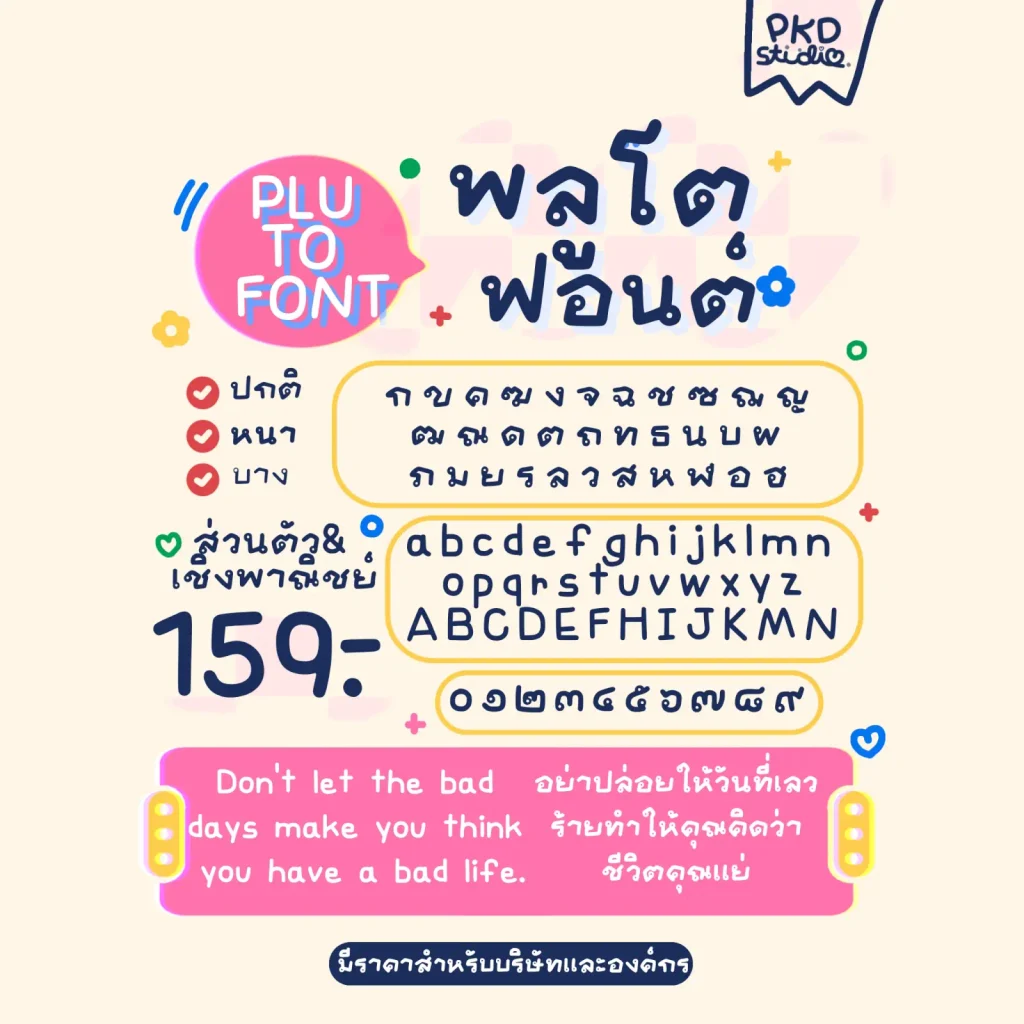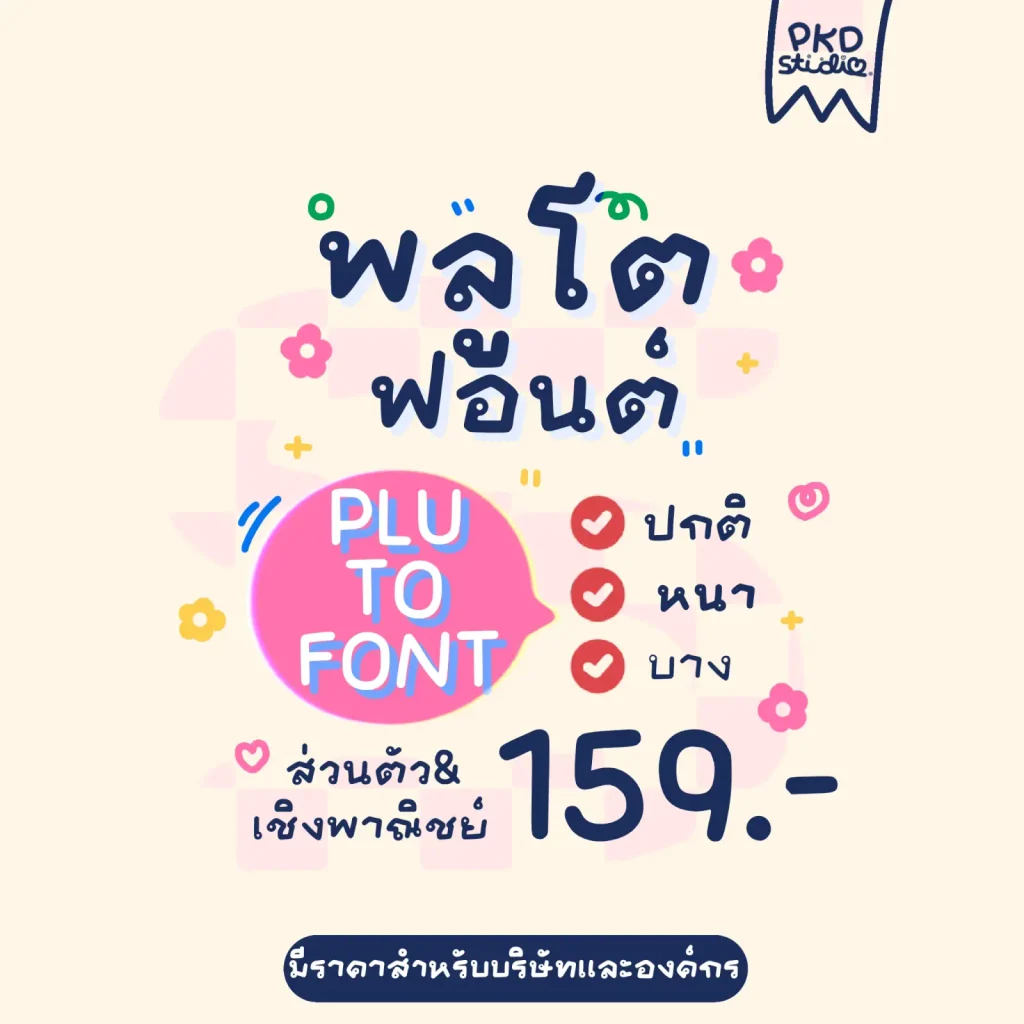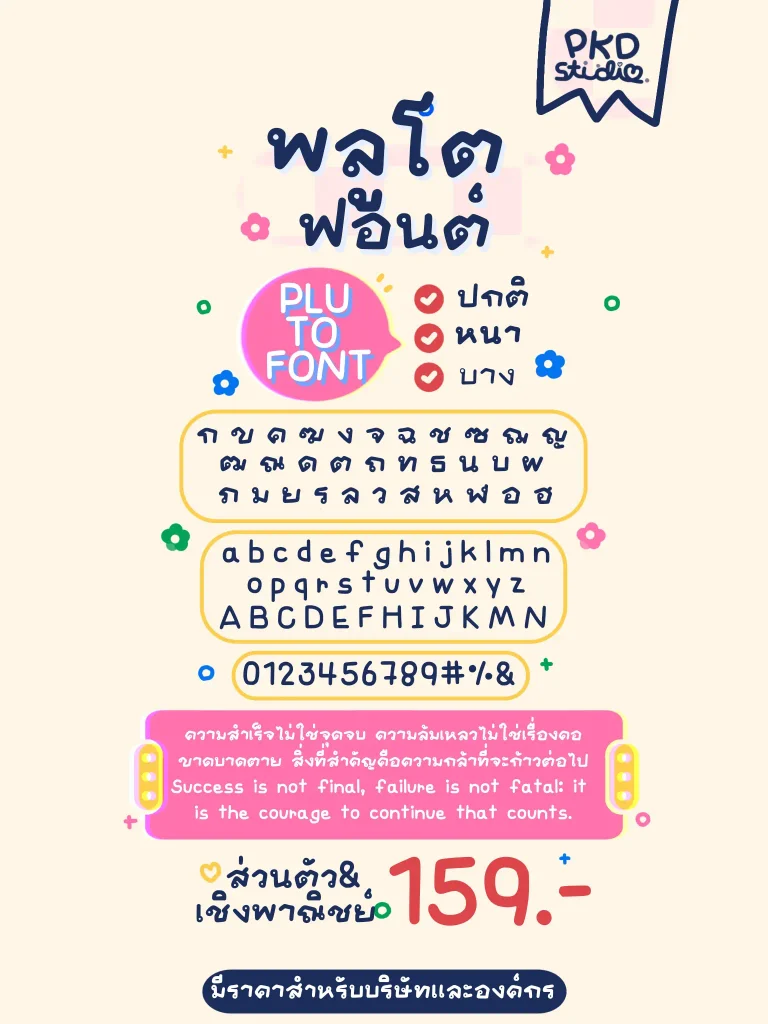
พลูโตฟอนต์ (PKD PLUTO) – ฟอนต์ลายมือน่ารัก สดใส เป็นกันเอง เหมาะสำหรับงานคอนเทนต์ โพสต์โซเชียล สติกเกอร์ คาเฟ่ และงานออกแบบทั่วไป
- รองรับภาษาไทย ภาษาอังกฤษ ตัวเลข และสัญลักษณ์
พลูโต (PKD PLUTO)